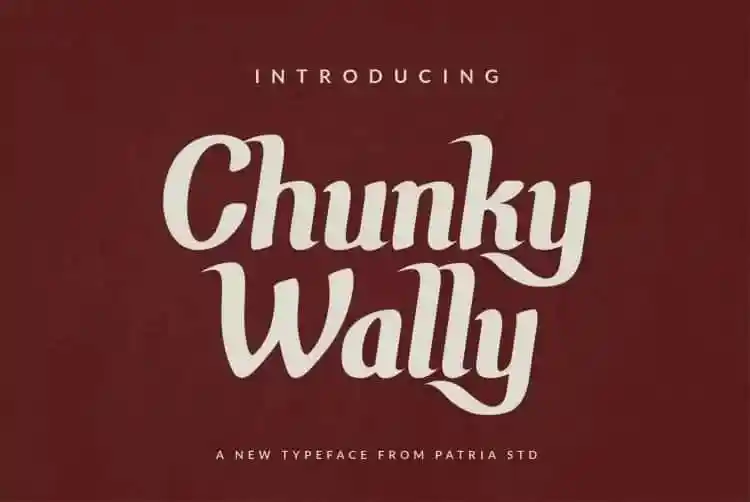
Chunky Wally Display Font – Download Grátis
A Fonte ‘Chunky Wally Display’ é uma escolha perfeita para quem busca um toque vintage e moderno no seu design. Criada pela Patria Ari Typestudio, esta fonte incorpora detalhes que remetem ao passado, mas se movimentam com elegância na corrente do tempo atual. Suas letras robustas e cheias de personalidade são perfeitas para qualquer projeto onde você deseja destacar a sua marca ou arte. O ‘Chunky Wally Display Font’ vem equipado com alternativas exuberantes que o tornam versátil, criando opções incríveis para usar em diferentes contextos. Seja em materiais impressos, design gráfico ou digital, esta fonte consegue manter uma consistência única e vibrante ao mesmo tempo em que oferece alegrias de personalização graças às suas alternativas. Para designers que buscam um toque vintage sem perder o brilho moderno, ‘Chunky Wally Display Font’ é uma excelente adição à sua biblioteca de fontes. Suas linhas robustas e seu design detalhado não só destacam a sua marca com elegância, como também permitem um toque único que faz toda a diferença em qualquer projeto gráfico.